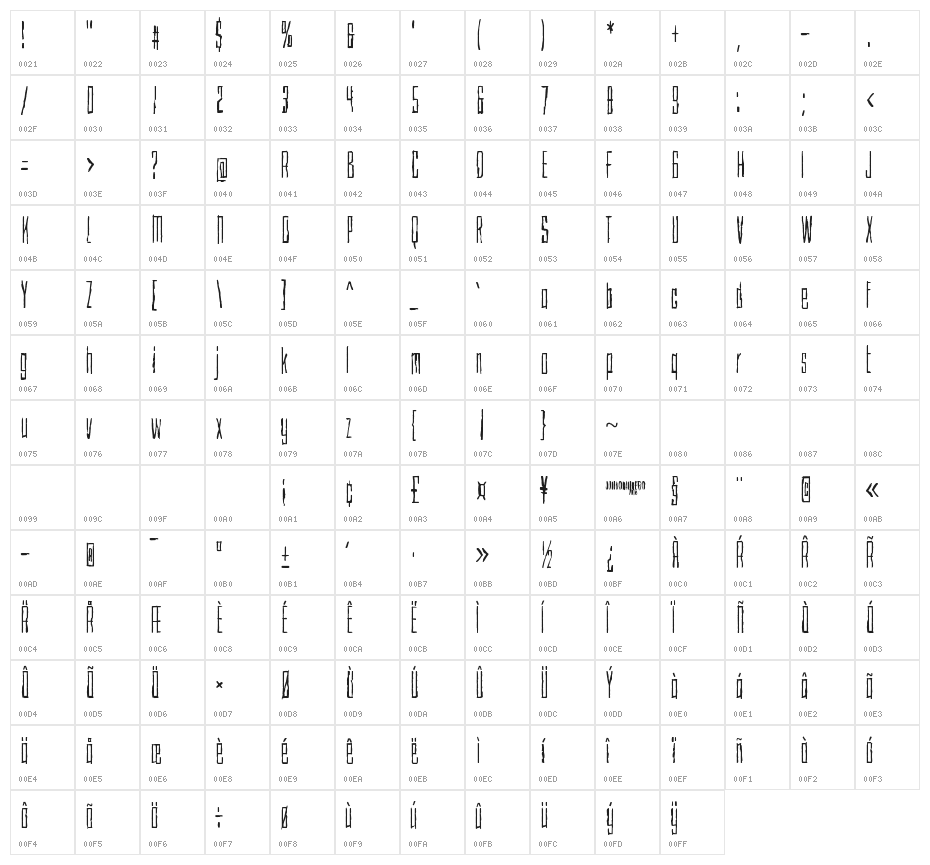
Cubebroken Font
| Рекомендуемые проекты | Ideal for posters, album covers, branding for edgy or artistic products, and any design needing a bold statement. |